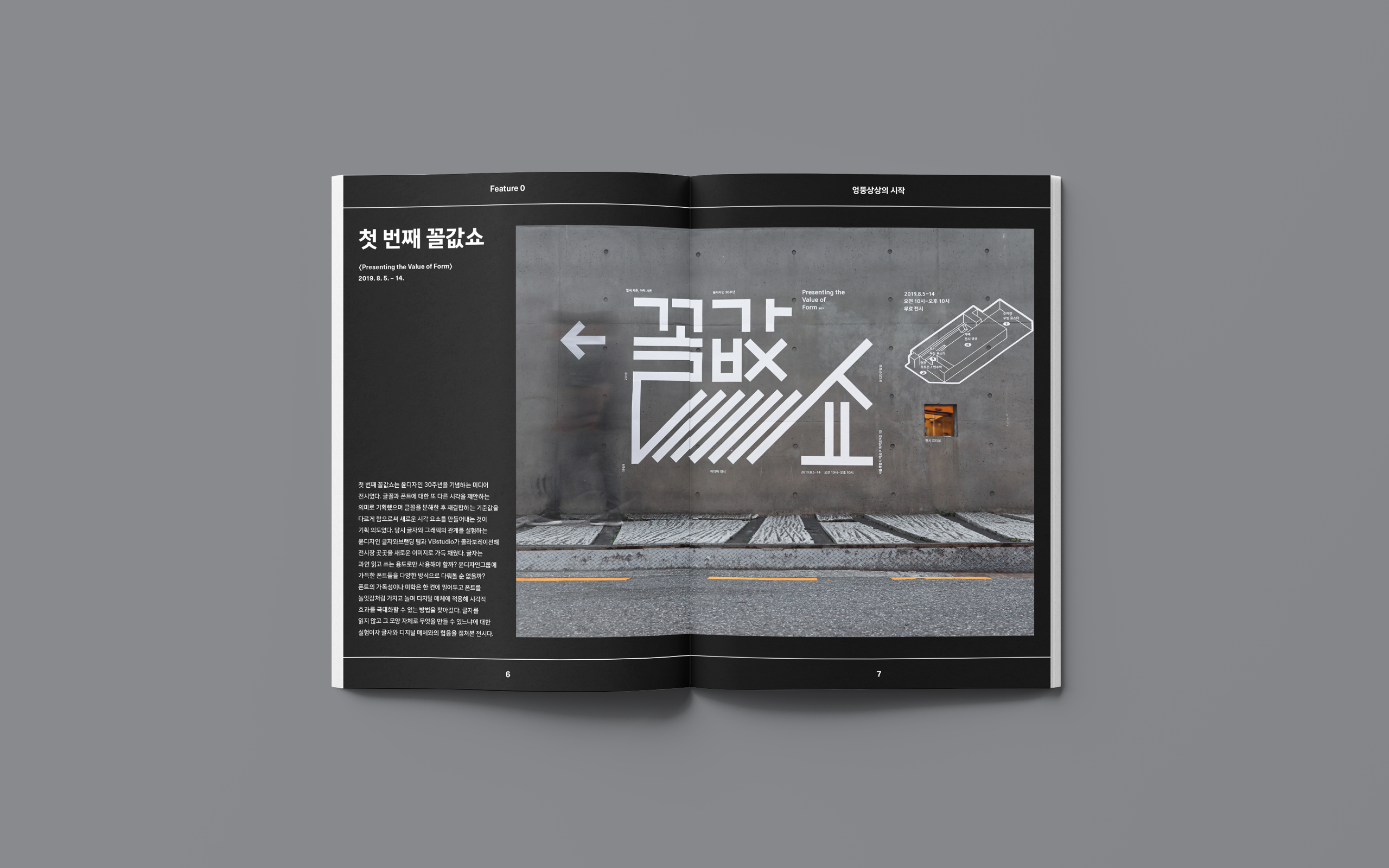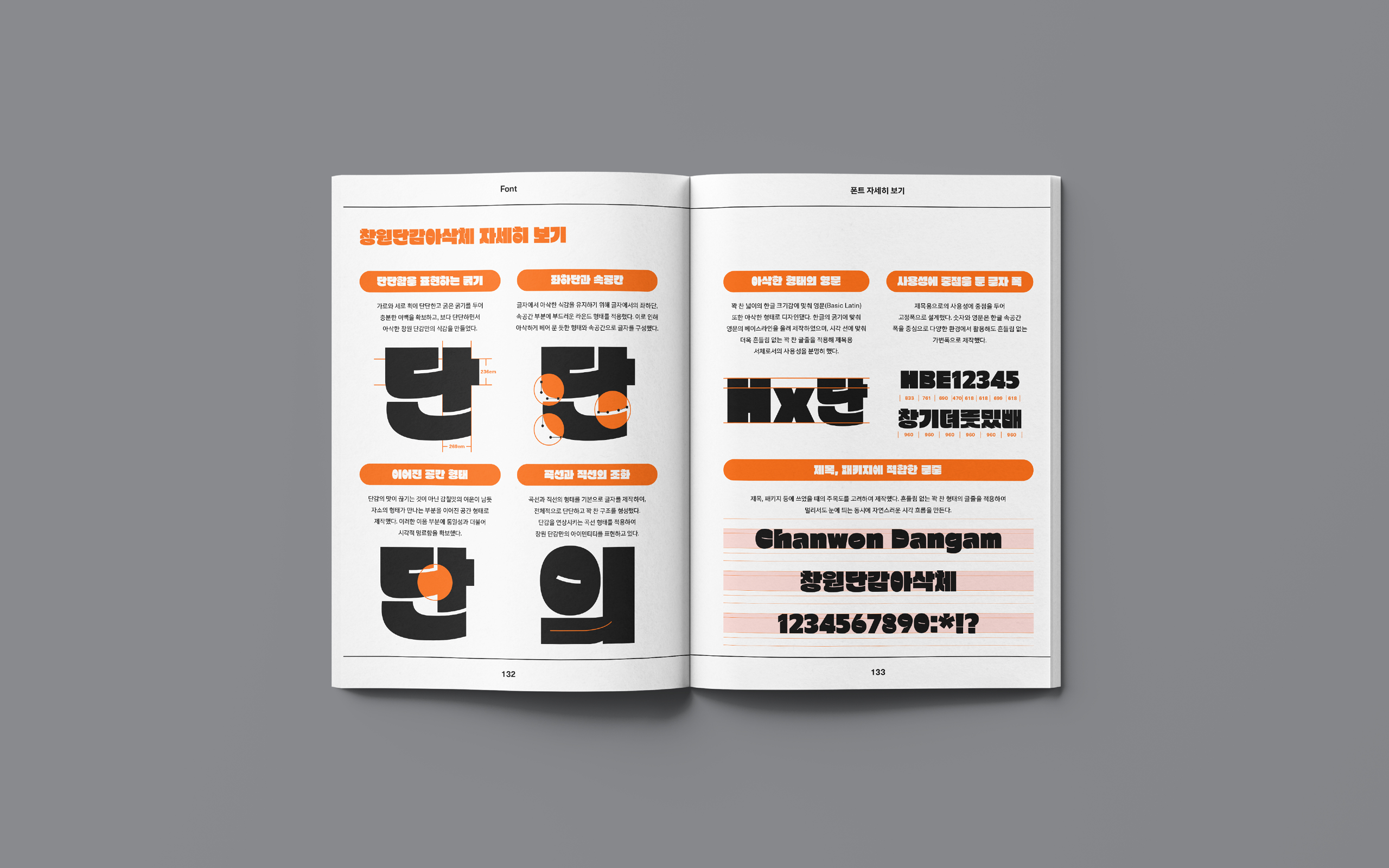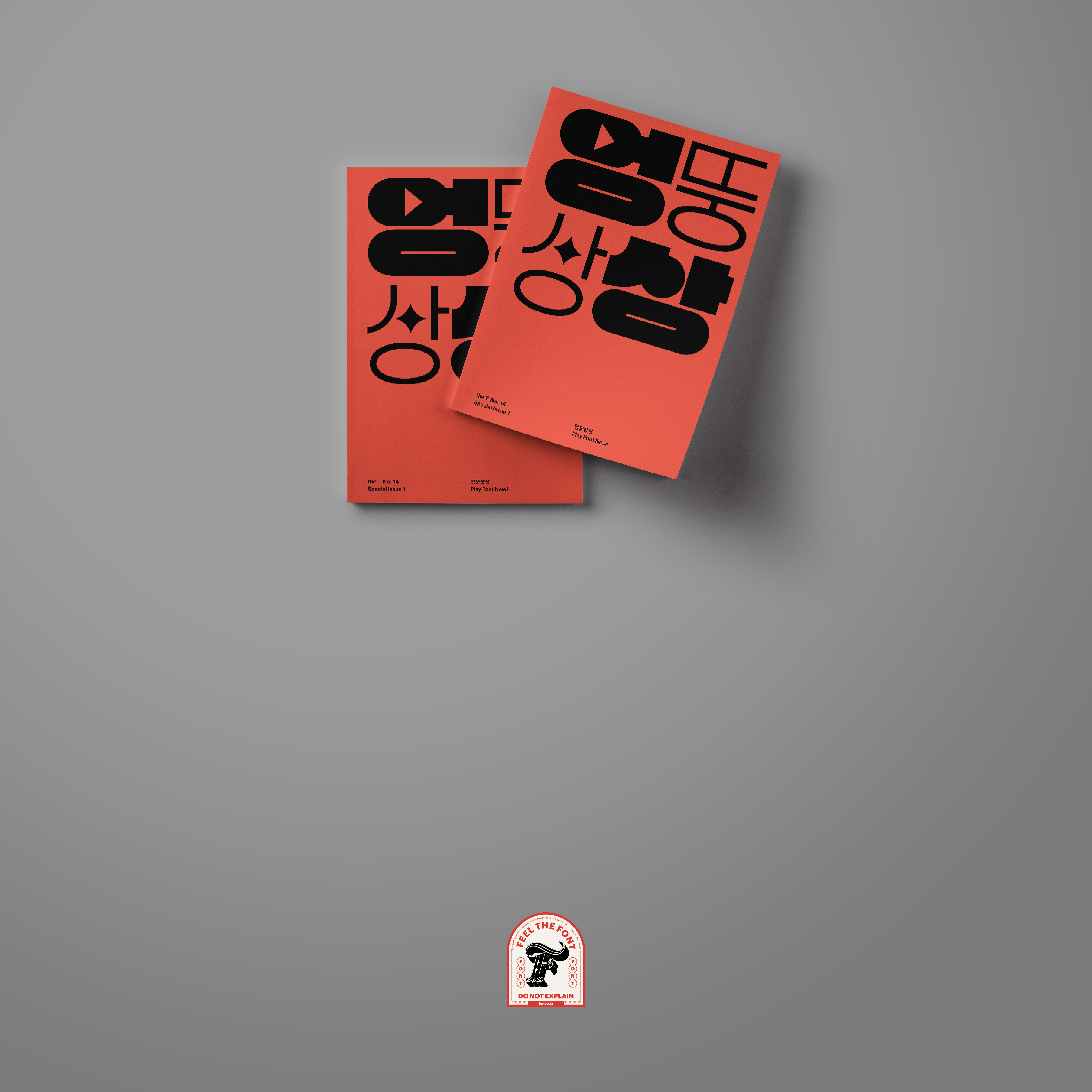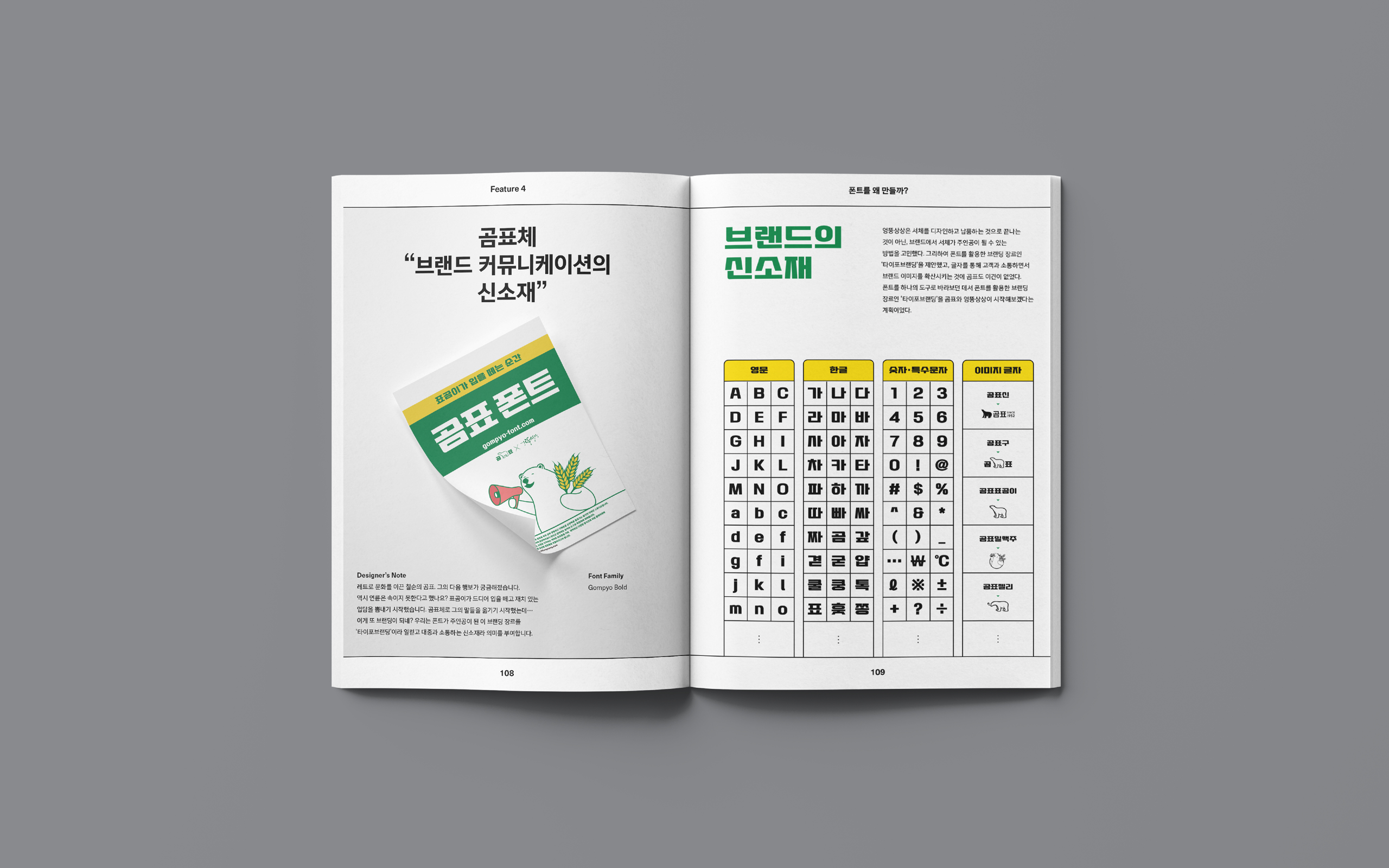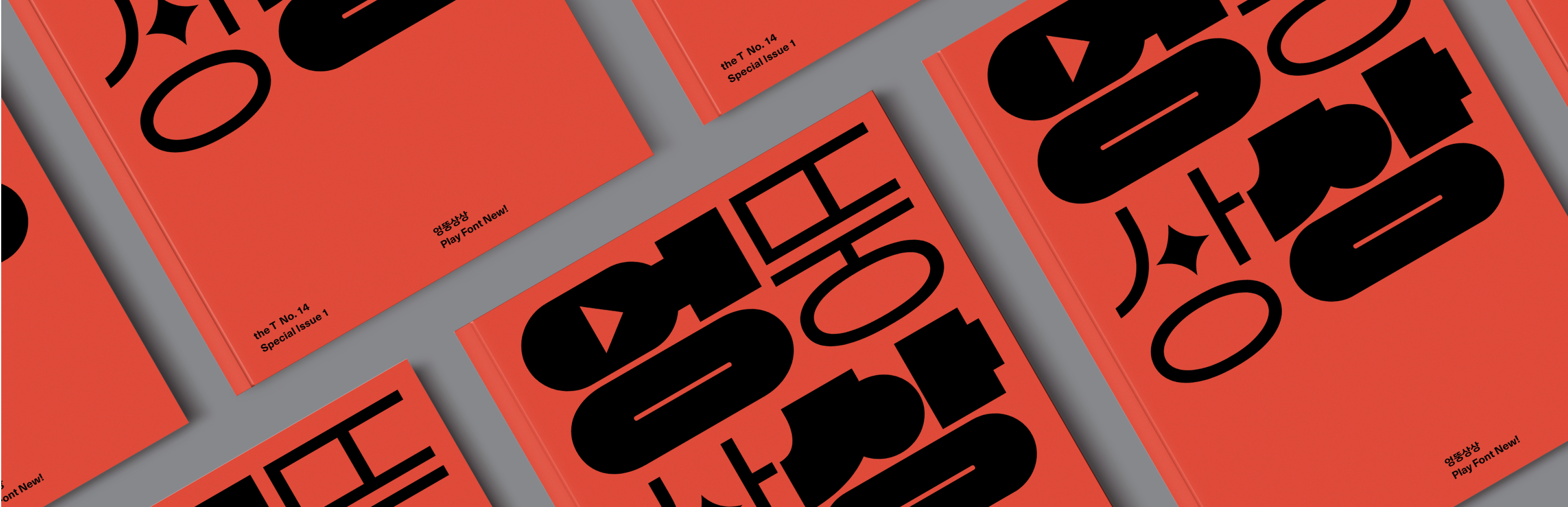
the T
No.14 / Special Issue 1.
엉뚱상상 Play Font New!
타입과 타이포그래피에 관한 이슈와 이야기, 다양한 관점의 생각들을 풍성하게
소개해온 매거진 〈the T〉가 특별판이라는 이름으로 오랜만에 독자들을 만납니다.
〈the T〉 14호인 동시에 특별판 1호를 표방하는 이번 호에서는 폰트로 무언가
새로운 시도를 지속하는 타이포브랜딩 스튜디오 ‘엉뚱상상’의 이야기를 소개합니다.
폰트가 주인공인 미디어 전시를 기획·실행하고, 숫자와 아이콘만으로 이루어진
엉뚱한 폰트를 제작하고, 폰트로 이슈메이커가 되는 방법을 궁리하며, 읽고 쓴다는
폰트의 역할을 넘어서는 색다른 폰트를 꿈꾸는! 수상하지만 활기찬 기운으로 가득한
스튜디오 엉뚱상상의 고군분투를 솔직하고 담백한 이야기로 엮어보았습니다.
폰트라고 하면 으레 떠올리는 작업을 벗어나고자 도전을 멈추지 않는 엉뚱상상의
액션 속에서 눈 밝은 독자 여러분이 새로운 폰트에 대한 영감과 비전을
발견할 수 있기를 바라봅니다.
Editor’s Note.
「the T」 특별판을 내며
Feature 0. 엉뚱상상의 시작
· 첫 번째 꼴값쇼
· 두 번째 꼴값쇼
· about 엉뚱상상
· Ideas : 우리의 상상은 엉뚱한 물음에서 시작한다
Feature 1. 디자이너만 폰트를 쓸까?
· 빅빅 넘버스 “크게 쓸수록 아름다운 숫자”
· 위트 아이콘 “빠른 퇴근을 위한 아이콘 자판기”
· WCG Play Font “게임처럼 즐기는 폰트”
· Images : 폰트로 새로운 시각꼴을 만들다
· Marketings : 폰트로 이슈메이커가 되는 방법
Feature 2. 새로운 세대를 위한 폰트는 무엇일까?
· 엉뚱상상체 “인터랙션 폰트 서비스”
· Opinion : 타이포그래피의 미래에 대한 사소한 단상_석재원
Feature 3. 글자를 읽고 쓸 수만 있을까?
· 콘트 “글자가 입을 떼는 순간”
· Essay : 글의 꼴, 마음의 모양_홍인혜
Feature 4. 폰트를 왜 만들까?
· 곰표체 “브랜드 커뮤니케이션의 신소재”
· 창원단감아삭체 “단감을 알리는 바이럴 마케팅 폰트”
· Font : 폰트 자세히 보기
· People : 엉뚱상상 메이커스
· Interview : 솔직히 말하자면
![]() | Feature 0. 엉뚱상상의 시작 : 첫 번째 꼴값쇼 엉뚱상상의 모태는 윤디자인그룹에서 글자와 그래픽의 관계를 실험하던 ‘글자와브랜딩’ 팀이었습니다. 이들은 윤디자인 창립 30주년을 맞이하여 폰트에 대한 기존의 시각을 벗어나 새로운 도약의 가능성을 점쳐보는 미디어 전시 ‘꼴값쇼’를 기획하고 실행하였습니다. 지면과 화면을 벗어나 공간 속에서 생동하는 폰트, 읽고 쓴다는 기능으로부터 벗어나 영상, 사운드와 조응하는 폰트. 기존 폰트에 대한 인식 틀을 깨뜨려보고자 했던 이들의 첫 시도는 여전히 스튜디오 엉뚱상상의 철학적, 경험적 밑바탕이 되어주고 있습니다. | |||
Feature 4. 폰트를 왜 만들까? : 곰표체 “브랜드 커뮤니케이션의 신소재” 엉뚱상상은 서체를 디자인하고 납품하는 것으로 끝나는 것이 아닌, 브랜드에서 서체가 주인공이 될 수 있는 방법을 고민했습니다. 그 결과 레트로 열풍을 이끈 칠순 브랜드 곰표와 협업하여 곰표체를 제작하고 “칠순 곰표, 늦은 나이에 입을 떼고 곰표체로 대화를 시작하다”라는 슬로건의 수다 프로젝트를 시작하게 됩니다. 이들의 협업은 “기업 전용 서체로 고객과 어떻게 대화할 것인가?”를 질문하고 고객 커뮤니케이션까지 디자인해보고자 했던 유의미한 도전이었습니다. | ![]() | |||
Feature 4. 폰트를 왜 만들까? : 창원단감아삭체 “단감을 알리는 바이럴 마케팅 폰트” 엉뚱상상은 전용 서체를 바라보는 새로운 시각을 제시하기 위해, 그 자체로 바이럴 마케터 역할을 해내는 전용 폰트 제작에 꾸준히 도전하고 있습니다. 단감하면 창원, 창원하면 단감이 절로 떠오르는 창원단감아삭체 제작기를 통해 마케팅의 도구가 된 폰트 이야기를 만나보세요. |